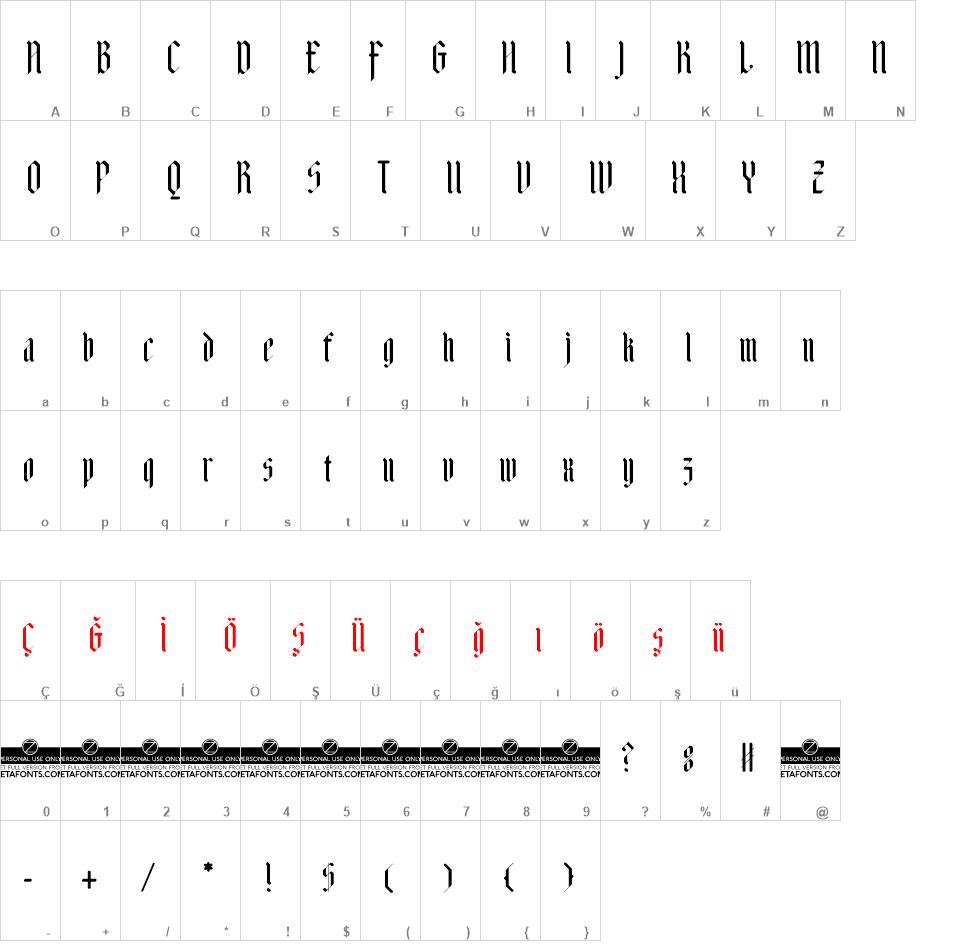
Adlibitum Font Family
Adlibitum wurde von Francesco Canovaro entworfen und ist ein Schriftformat, das als zeitgemäßes Restyls alter textura-medioevaler Befehlszeichen entworfen wurde. Es hat einen starken vertikalen Akzent und ein geometrisches Design mit 45-Grad-Winkeln und weichen abgerundeten Ecken. Es bietet Unterstützung für offene Schriftarten für eine Vielzahl von Zeichen und Buchstaben, die für drei Strichstärken und europäische Sprachen unterstützt werden.